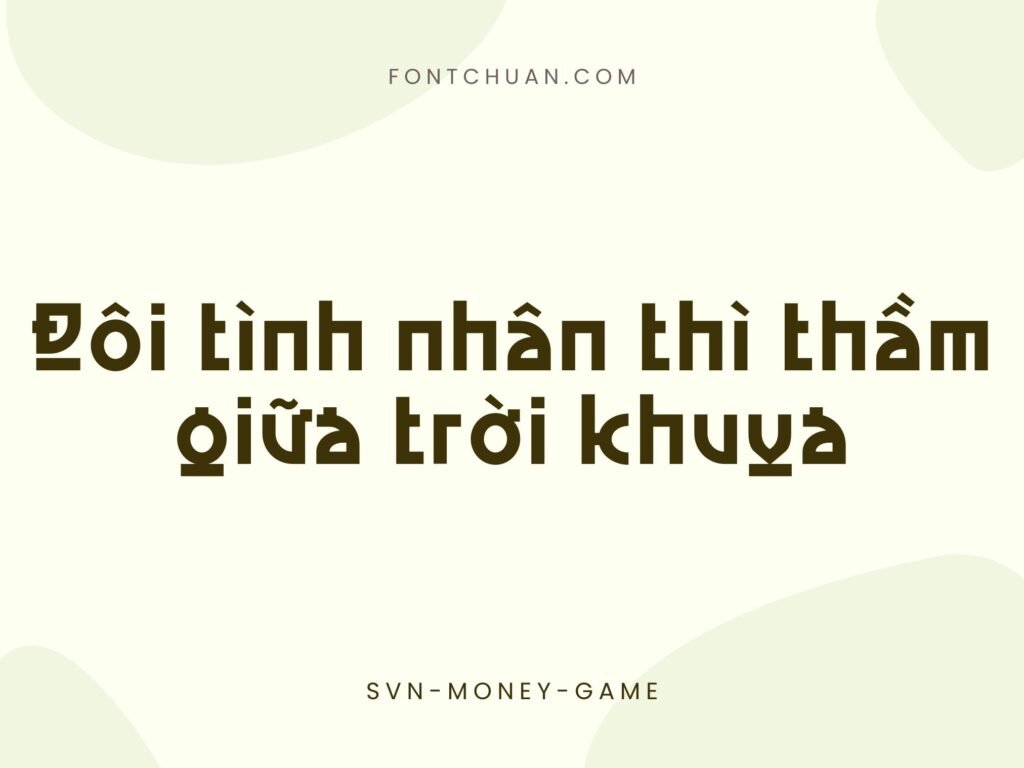
Font SVN Money Game Việt Hóa
Tác giả Font: Pollux Of Geminorum
Font SVN Money Game là phiên bản Việt hóa của kiểu chữ Money Game, được thực hiện bởi STYLEno.1 Fonts. Money Game là một kiểu chữ hiển thị lấy cảm hứng từ các bộ phim Hàn Quốc nổi tiếng, mang phong cách hiện đại, trẻ trung và táo bạo. Thiết kế của font thể hiện nét cá tính rõ ràng, đặc biệt phù hợp với các nội dung truyền thông mạnh mẽ như poster phim, video YouTube, tiêu đề mạng xã hội hay các dự án branding. Font bao gồm đầy đủ các ký tự chữ hoa, chữ thường, chữ số và dấu câu, hỗ trợ đa ngôn ngữ. Tính thẩm mỹ của Money Game giúp các nhà thiết kế thể hiện cá tính sáng tạo và thu hút sự chú ý hiệu quả. Ngoài ra, font này cũng có thể được sử dụng như một Font chữ Giáng Sinh, lý tưởng cho các poster, banner hay thiệp mùa lễ hội, mang đến không khí vui tươi, rực rỡ cho các sản phẩm thiết kế.
SVN Money Game lý tưởng cho các dự án thiết kế cần sự đột phá và phong cách hiện đại, như tiêu đề poster, banner sự kiện, bao bì sản phẩm, truyền thông số hoặc quảng cáo. Các ngành nghề như quảng cáo, công nghệ và giáo dục có thể tận dụng font này để tạo dấu ấn trực quan. Ngoài ra, font cũng rất phù hợp với các dịp như Tết, Giáng sinh, Valentine và các lễ hội truyền thống khác.